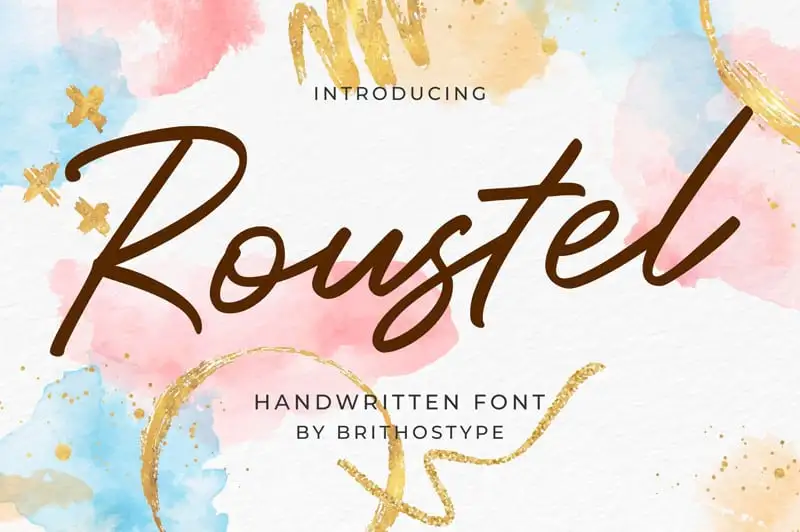
Roustel Handwritten Font – Download Grátis
A Roustel Handwritten Font é uma elegante fonte aquarela que destaca sua personalidade em qualquer projeto. Seu design artesanal cria um efeito único, perfeito para criar logomarcas ou modelos de template, cartões de convite, blogs, marcações, capas de livros, revistas, anúncios, papelaria e desenhos de logotipo. Esta fonte inclui um conjunto básico de letras e alternativas, assim como números, frações, símbolos e pontuação básica. Perfeito para designers digitais e editoriais, a Roustel Handwritten Font é perfeita para criar designs profissionais ou artesanais. Seja você criando uma tagline para sua marca ou capa de um livro que deseja tornar único com seu estilo de escrita autêntica, há algo nesta fonte para todos. Aqui está a oportunidade de dar vida à sua identidade visual e torná-la ainda mais única e especial.